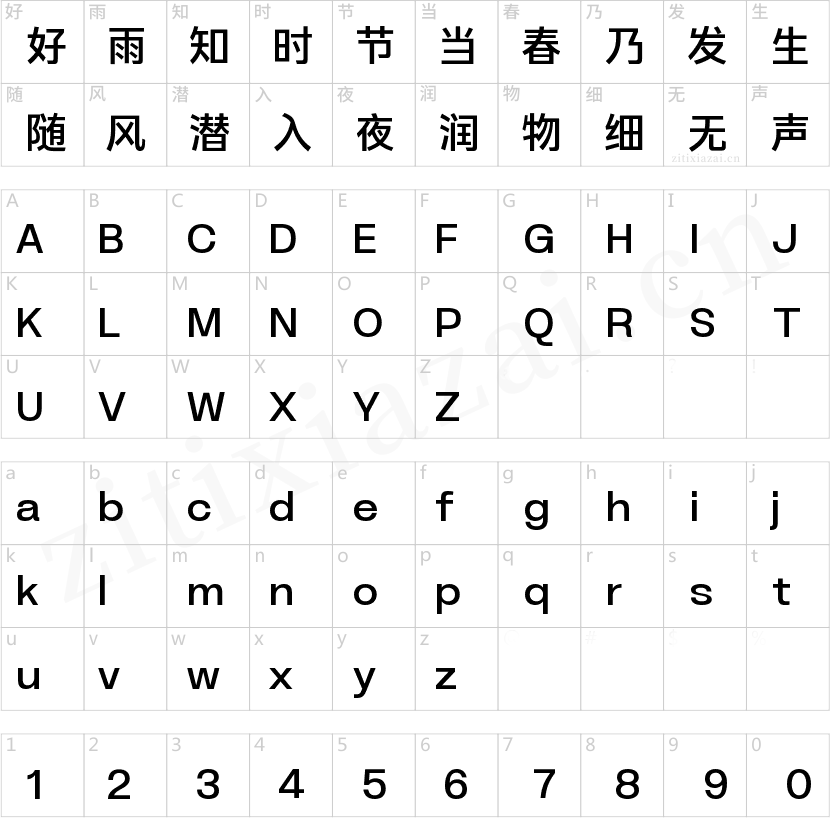
字魂大黑-Medium
字魂大黑-Medium,这款字体结构工整、笔画清晰,兼顾美观与易读性,适用于标题、正文、海报、包装、LOGO 等多种场景。字形优雅稳定,风格百搭耐看,适配日常排版与创意设计,让文字呈现更舒适、更具质感。字魂大黑-Medium一笔一画,皆是细节,以均衡的比例、流畅的线条打造舒适视觉体验,字形端正大气,风格简约现代。无论是商业设计、品牌宣传还是日常排版,都能轻松驾驭,让文字更有格调与力量。字魂大黑-Medium字体下载。